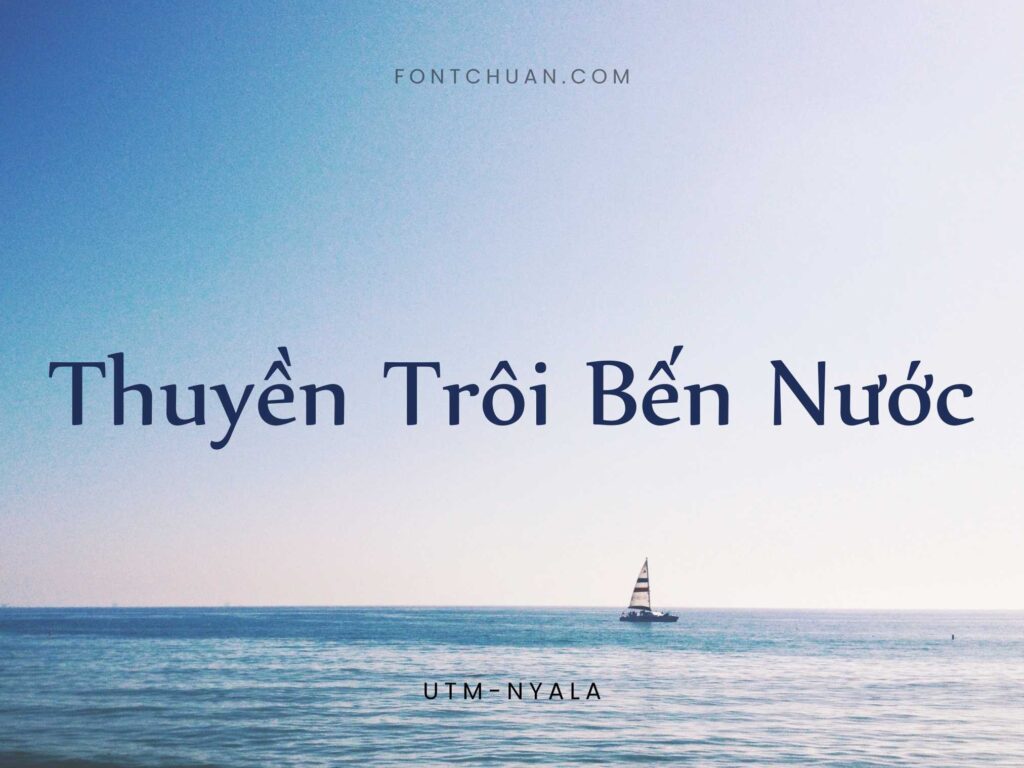
Font UTM Nyala Việt Hóa
UTM Nyala là một font chữ serif hiện đại, mang phong cách thanh lịch với các đường nét mềm mại và chuyên nghiệp. Font này mang đến cảm giác trang nhã, phù hợp với nhiều mục đích sử dụng từ in ấn đến thiết kế đồ họa. Font đã được Việt hóa để hỗ trợ tiếng Việt, giúp mở rộng khả năng ứng dụng. Thành viên của Font Chuẩn đã sưu tầm và giới thiệu font này nhằm đáp ứng nhu cầu bạn đọc, cung cấp nguồn tham khảo chất lượng và ứng dụng thực tế vào các dự án thiết kế
Về đặc điểm thiết kế, UTM Nyala có kiểu dáng serif nhẹ, độ dày vừa phải và độ tương phản hài hòa, giúp nâng cao tính thẩm mỹ và khả năng đọc. Font này phù hợp với nhiều ứng dụng như thiết kế logo, tài liệu in ấn, sách, bao bì sản phẩm và nội dung thương hiệu. Các ngành nghề như quảng cáo, giáo dục, công nghệ và thiệp cưới có thể tận dụng font này để tạo nên sự sang trọng và chuyên nghiệp trong các ấn phẩm thiết kế